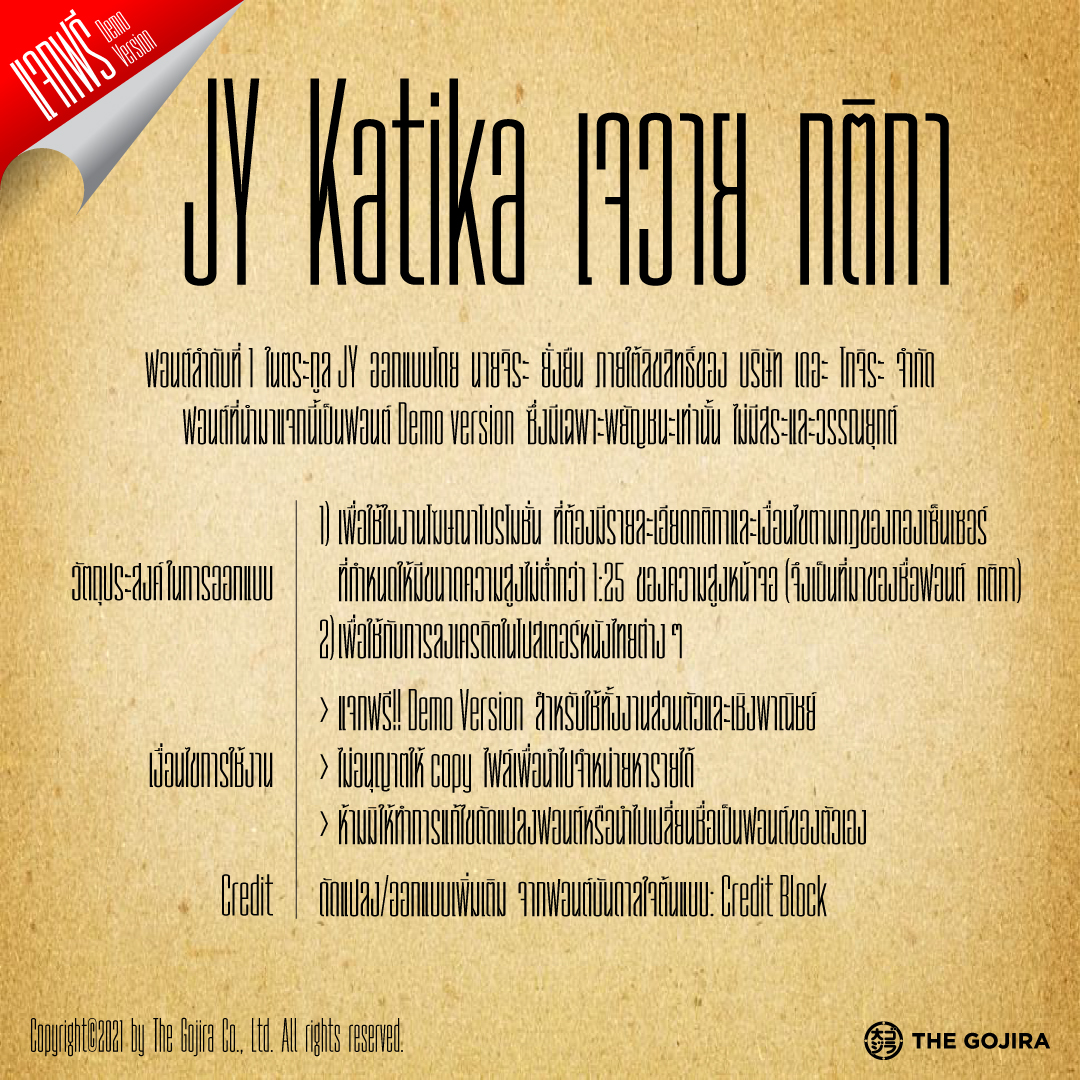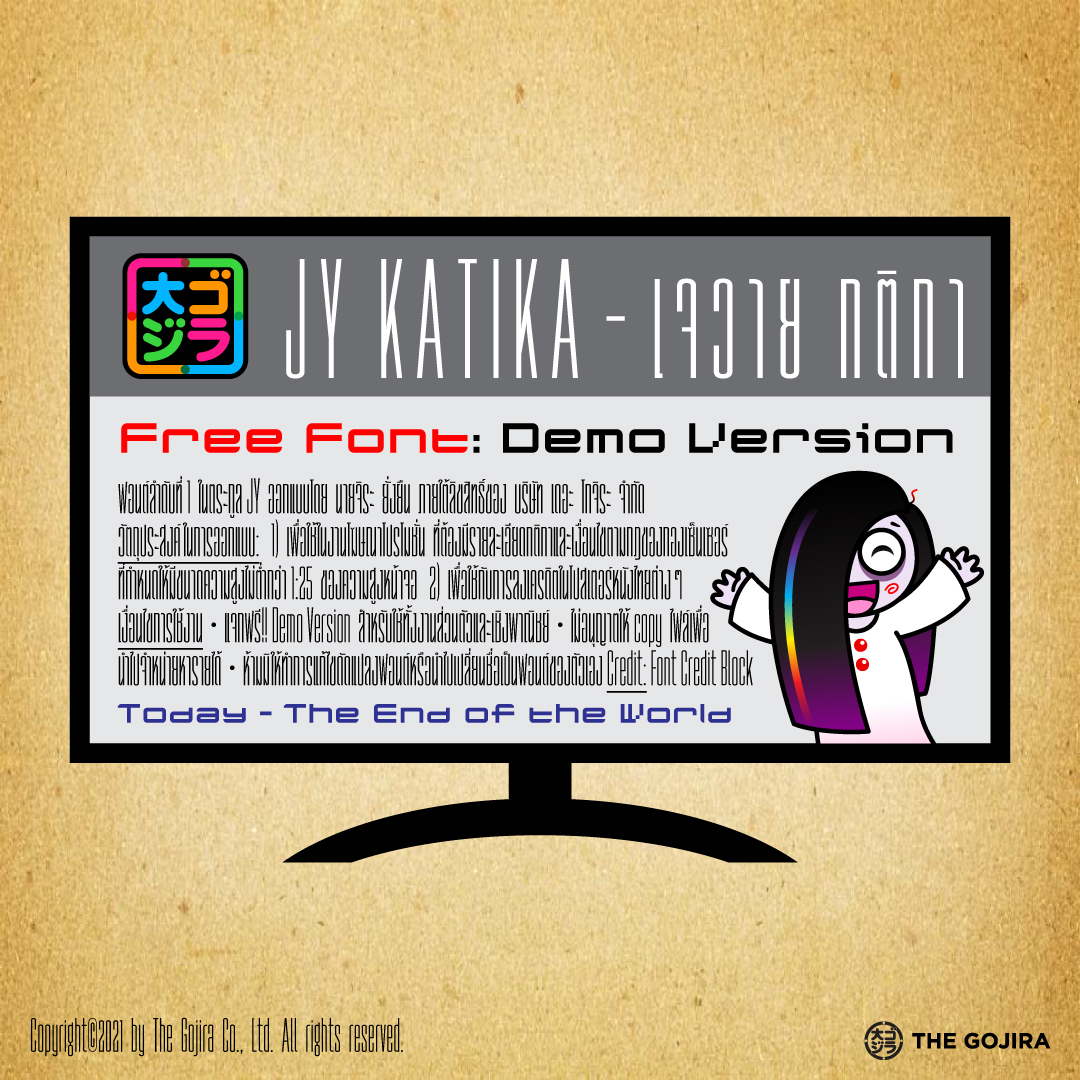
เจวาย กติกา (JY Katika)
JY Katika อ่านว่า เจวาย กติกา
ฟอนต์ลำดับที่ 1 ในตระกูล JY ออกแบบโดย นายจิระ ยั่งยืน ภายใต้ลิขสิทธิ์ของ บริษัท เดอะ โกจิระ จำกัด
ฟอนต์ที่นำมาแจกนี้เป็นฟอนต์ Demo version ซึ่งมีเฉพาะพยัญชนะเท่านั้น ไม่มีสระและวรรณยุกต์
วัตถุประสงค์ในการออกแบบ:
1) เพื่อใช้ในงานโฆษณาโปรโมชั่น ที่ต้องมีรายละเอียดกติกาและเงื่อนไขตามกฎของกองเซ็นเซอร์
ที่กำหนดให้มีขนาดความสูงไม่ต่ำกว่า 1:25 ของความสูงหน้าจอ (จึงเป็นที่มาของชื่อฟอนต์ กติกา)
2) เพื่อใช้กับการลงเครดิตในโปสเตอร์หนังไทยต่างๆ
ปรับปรุงและออกแบบเพิ่มเติม จากฟอนต์บันดาลใจต้นแบบ: Credit Block